Font chữ là một trong những yếu tố cốt lõi của thiết kế. Lựa chọn font chữ nào, kết hợp các font chữ như thế nào là các câu hỏi mà designers cần trả lời trước khi bắt đầu thiết kế. Trong bài viết này, Viện CNTT ITPlus sẽ hướng dẫn bạn một số cách kết hợp font chữ đơn giản nhất nhé.
Đây là quy tắc đầu tiên khi bạn lựa chọn font chữ cho thiết kế. Thông thường thiết kế của bạn chỉ nên có 2 loại font chữ, trong một số ít trường hợp bạn mới sử dụng 3 loại font chữ. Nếu bạn sử dụng nhiều hơn 3 font chữ thì thiết kế dễ dàng trở rối mắt, thiếu chuyên nghiệp
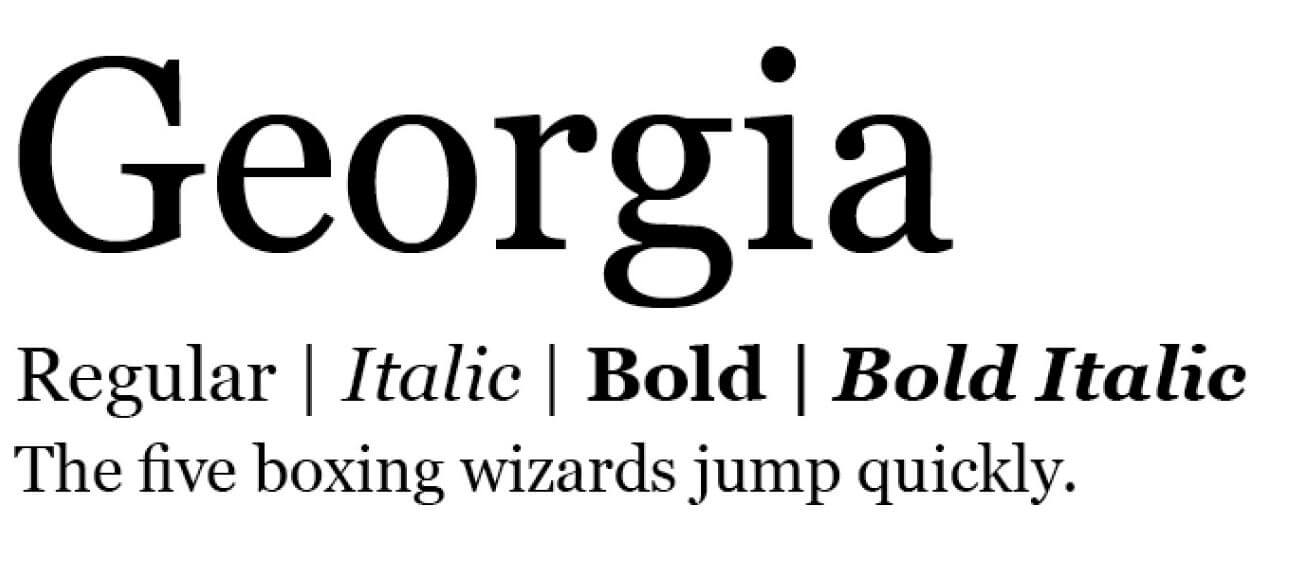
Ví dụ: Font Georgia thuộc họ Serif có chân kết hợp với font Helvitica thuộc họ San Serifs không chân.
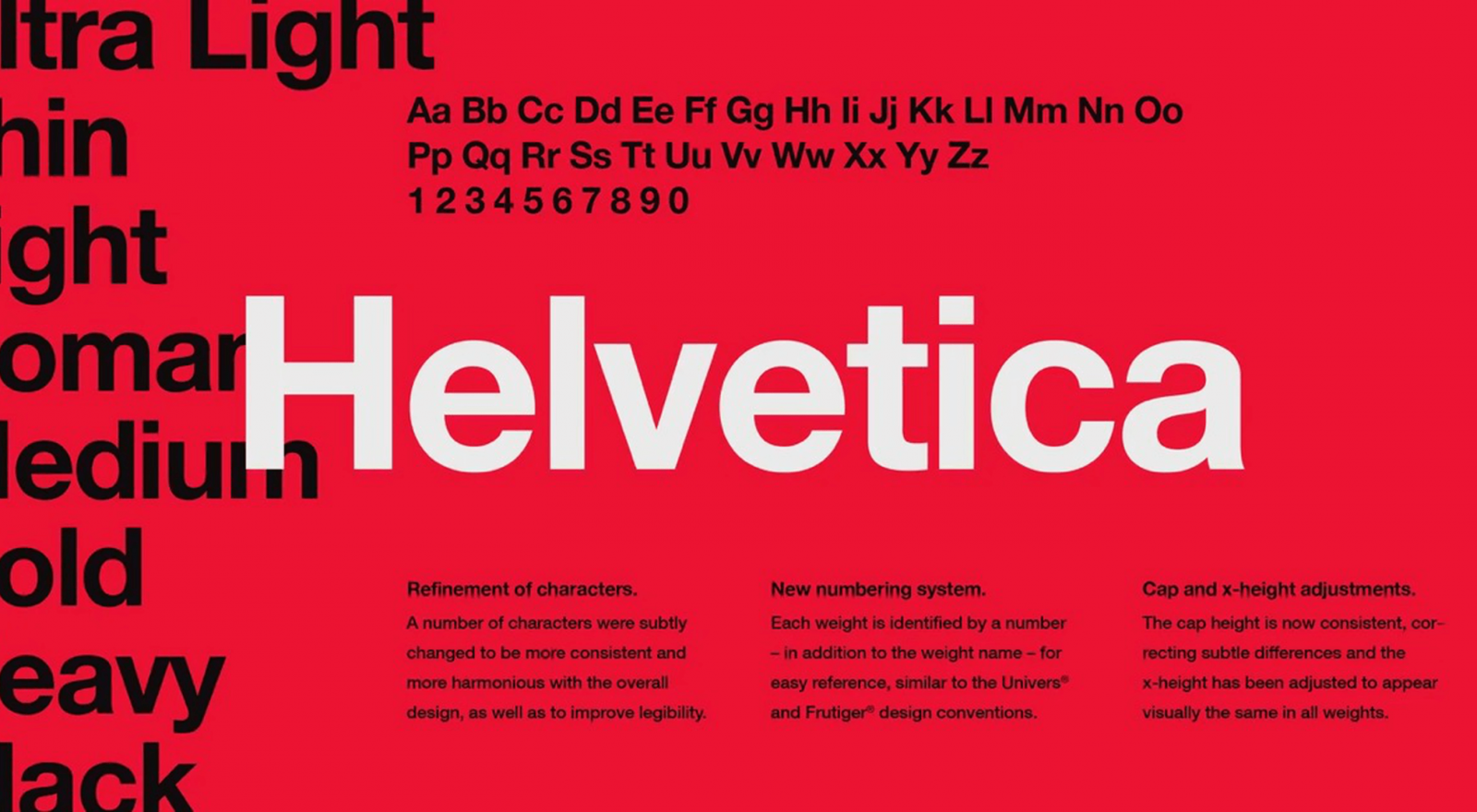
Mục tiêu của bạn khi chọn 2 hay 3 font chữ cho thiết kế là để làm nổi bật thông tin nào đó hoặc đó tách riêng vai trò của từng nội dung trong thiết kế. Vì vậy nếu bạn sử dụng 2 font chữ quá giống nhau thì hiệu quả đó không đạt được đồng thời còn gây khó chịu cho mắt người nhìn.
Ví dụ font chữ Times New Roman và font chữ Palatino khá giống nhau và nên bạn không nên sử dụng chúng cùng trong 1 thiết kế.
Cách đơn giản nhất là bạn chọn 2 font chữ có sẵn độ tương phản như ví dụ về họ Serif và họ San Serifs, 2 kiểu font chữ này tương phản nhau về thiết kế có chân hay không chân. Ngoài ra, thông thường chúng ta có thể lựa chọn 1 font để làm tiêu đề và bôi đậm font đó để đạt được hiệu quả tương phản cao.
Phương pháp đơn giản nhất để xác định xem chúng có độ cao bằng nhau không là chồng 2 font chữ lên nhau. Việc đảm bảo 2 font chữ có độ cao bằng nhau là cần thiết vì điều này đảm bảo tính chuyên nghiệp và đồng nhất của thiết kế.